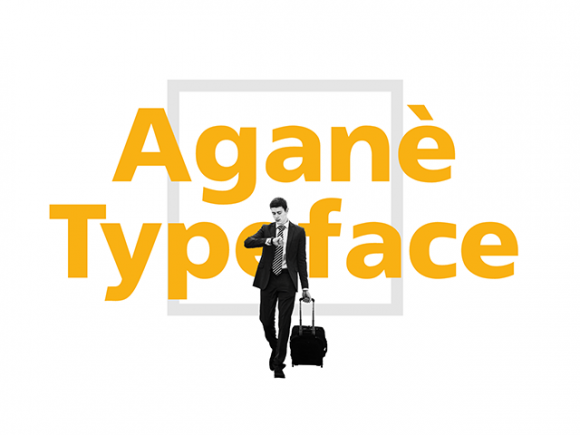
A Aganè Font Family é uma nova família de fontes sans serif criada por Danilo De Marco. Esta fonte faz homenagem a Adrian Frutiger e Bob Noorda, dois profissionais que deixaram marcas indeléveis na história da tipografia, especialmente em suas famosas séries Frutiger e Avenir. O designer oferece Aganè gratuitamente para todos os usuários. Com quatro estilos distintos, esta família de fontes é perfeitamente ideal para uso em design de interface do usuário, graças à sua leitura clara e fluida. Seja você um profissional ou amante da tipografia, não há dúvida de que Aganè oferecerá uma maneira moderna de expressar seu trabalho.